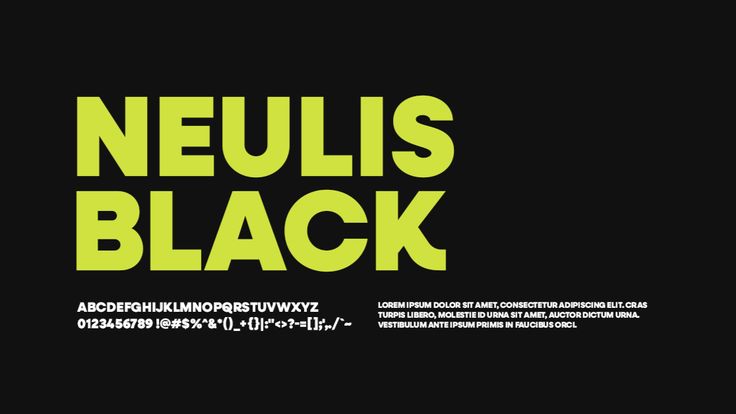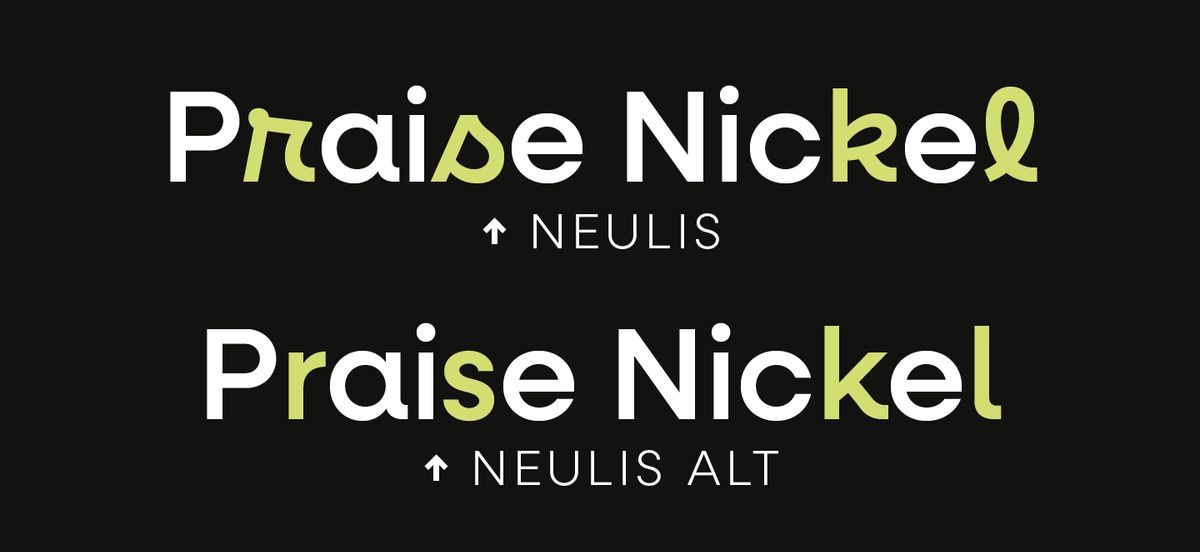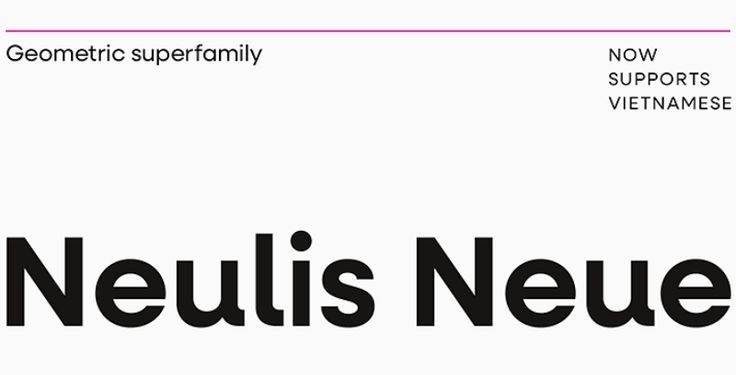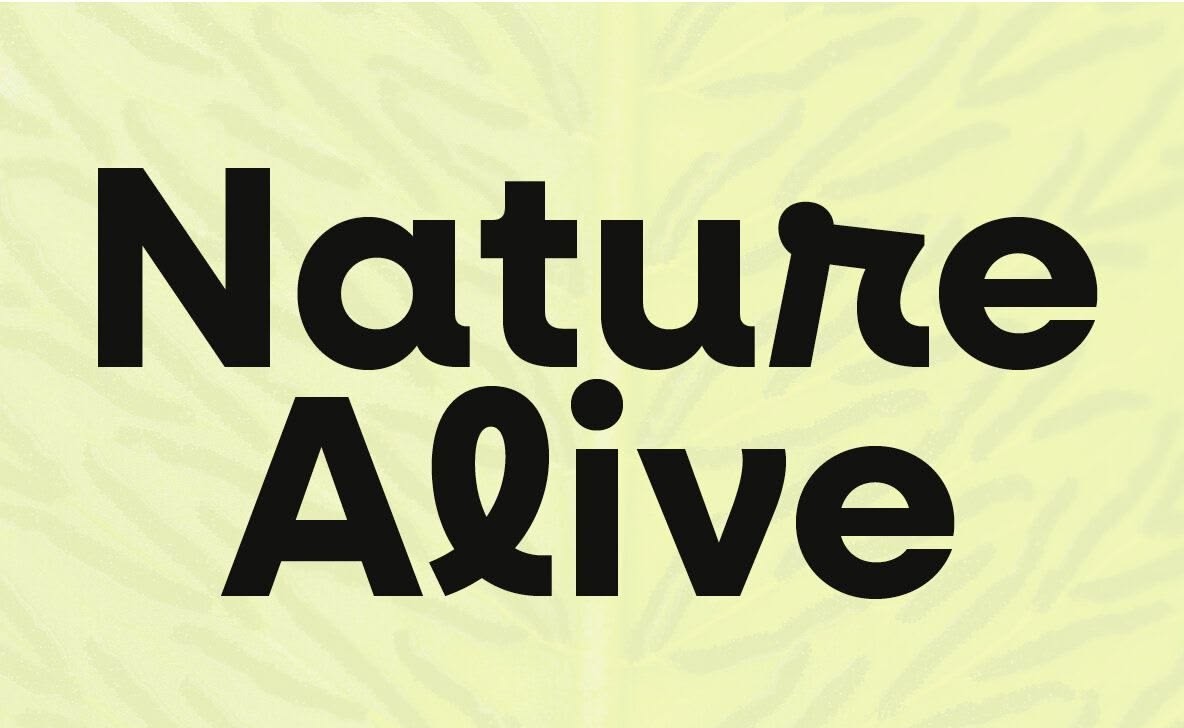
Font Neulis là gì?
Neulis là một bộ font chữ hiện đại thuộc dòng Sans-serif, được thiết kế với phong cách tối giản nhưng không kém phần thanh lịch. Đặc trưng của font Neulis-neue là các đường nét hình học cân đối, độ dày nét vừa phải, tạo cảm giác dễ đọc và tinh tế cho người xem. Đây là sự lựa chọn tuyệt vời cho các dự án nhận diện thương hiệu công nghệ, mỹ phẩm hoặc các ấn phẩm văn phòng đòi hỏi sự trẻ trung.
Phiên bản Neulis Neue là sự cải tiến vượt bậc về độ tương phản và khoảng cách ký tự (kerning), giúp các văn bản dài trông thoáng đãng hơn. Tuy nhiên, bản gốc thường không hỗ trợ tiếng Việt, dẫn đến việc các nhà thiết kế Việt Nam gặp khó khăn khi gõ dấu. Bản font Neulis việt hóa mà chúng tôi cung cấp đã được tinh chỉnh kỹ lưỡng từng dấu mũ, dấu thanh để đảm bảo tính đồng nhất với các ký tự gốc.
Ứng dụng font Neulis việt hóa trong thiết kế và in ấn
Nhờ phong cách hiện đại, font Neulis được ứng dụng linh hoạt trong nhiều ấn phẩm và bao bì doanh nghiệp:
- Thiết kế bao bì mỹ phẩm và dược phẩm: Sự sạch sẽ của font Neulis giúp các thông tin thành phần, công dụng trên vỏ hộp giấy trở nên dễ đọc, mang lại cảm giác tin cậy cho khách hàng.
- Sản xuất túi giấy in logo thương hiệu: Font chữ này thường được dùng cho các slogan hoặc địa chỉ công ty in trên túi Kraft hoặc Ivory, tạo điểm nhấn chuyên nghiệp và sang trọng.
- In ấn sản phẩm cho văn phòng: Neulis rất phù hợp để in lên bình giữ nhiệt, sổ tay hoặc bút ký nhờ các nét chữ rõ ràng, bền màu khi thực hiện công nghệ in UV hoặc khắc laser.
- Xây dựng bộ nhận diện sự kiện: Từ thiệp mời đến backdrop, font Neulis việt hóa giúp các thông điệp truyền tải một cách trực diện, mạnh mẽ và đầy cá tính.